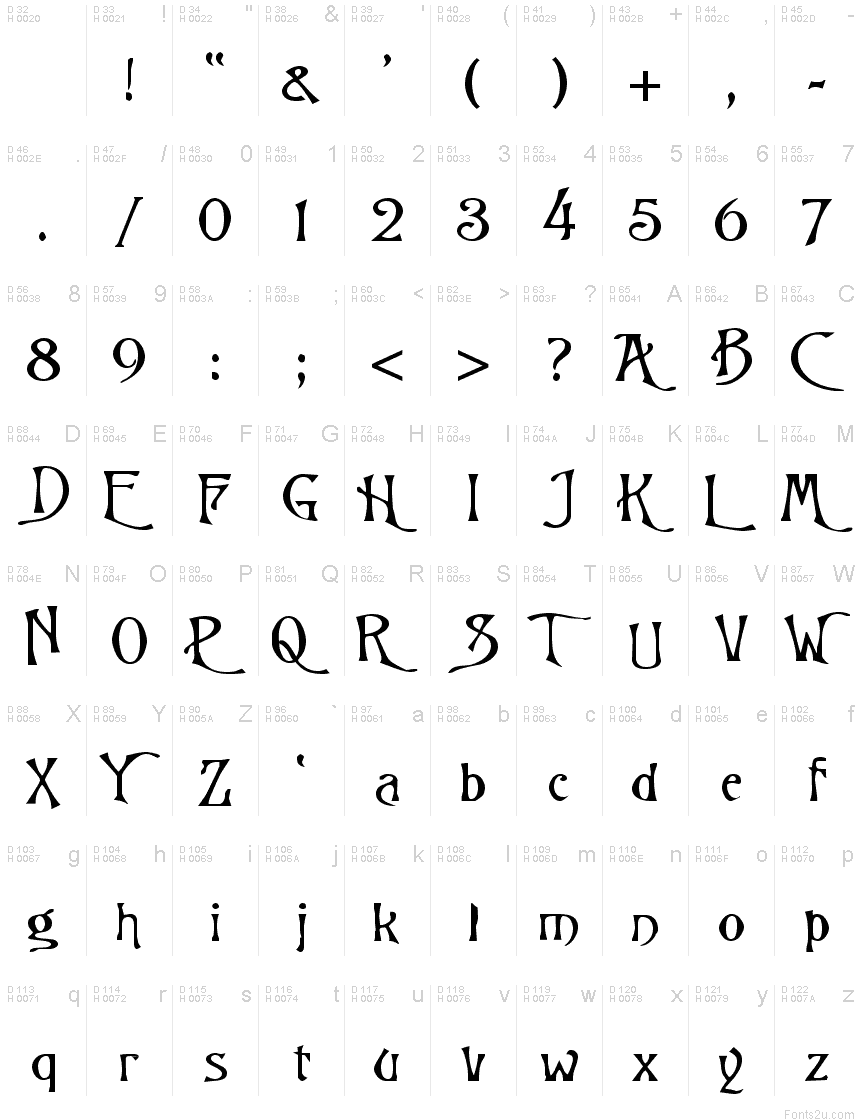
Wizard Extended, od SWFTE International, to darmowy krój fantasy-gothic o klimacie średniowiecznych baśni. Litery łączą wysokie, zwężające się pociągnięcia z ostrymi, haczykowatymi szeryfami oraz kilkoma miękkimi, niemal kaligraficznymi krzywiznami, dzięki czemu czcionka nabiera teatralnego, a nie surowego wyrazu. Sprawdzi się na okładkach książek fantasy, w tytułach gier, nagłówkach plakatów, tematycznych opakowaniach i grafikach eventowych, wszędzie tam, gdzie potrzebny jest klimat starego grymuaru bez konieczności sięgania po pełną czcionkę blackletter. Jako darmowy font, świetnie nadaje się również do krótkiego brandingu, otwierania rozdziałów czy logotypów – wyraziste punkty i zamaszyste linie nadają nawet krótkim tekstom wyczarowany, magiczny charakter.